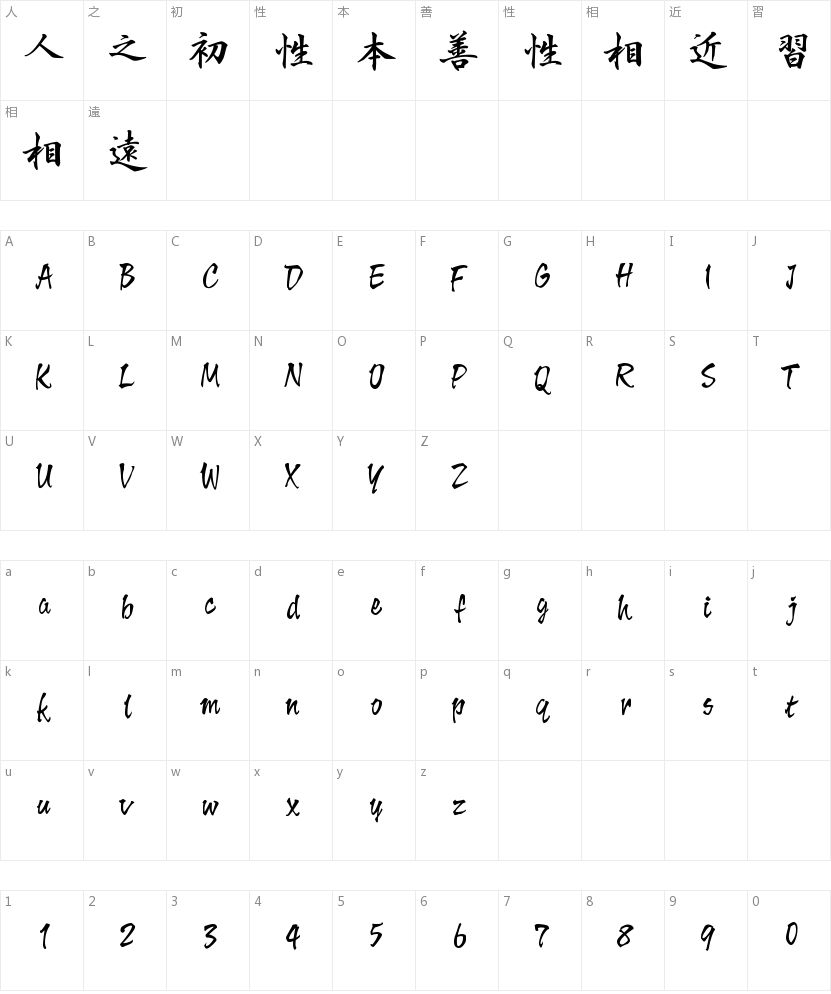
方圆流丽行书粗繁体
方圆流丽行书粗繁体字体是一款比较流行的繁体字体,它的特点是字体粗犷大方,直笔折行,笔画清晰,结构清楚,笔画连续,笔画粗细均匀,字形美观,结构严谨,笔画精细,结构清晰,笔画细腻,结构精细,构图精致,笔画活泼,构图活泼,字形精致,笔画流畅,构图精美,字形美观,笔画流畅,构图精美,字形精致,且字体较为清晰,较为易读,同时也具有良好的空间感,让文字更加美观大方。
方圆流丽行书粗繁体是一款非常不错的手写艺术字体,具有很好的视觉感,适合于文化类的宣传设计、商业类品牌的广告和产品包装设计以及个性化文字排版等较多场景。